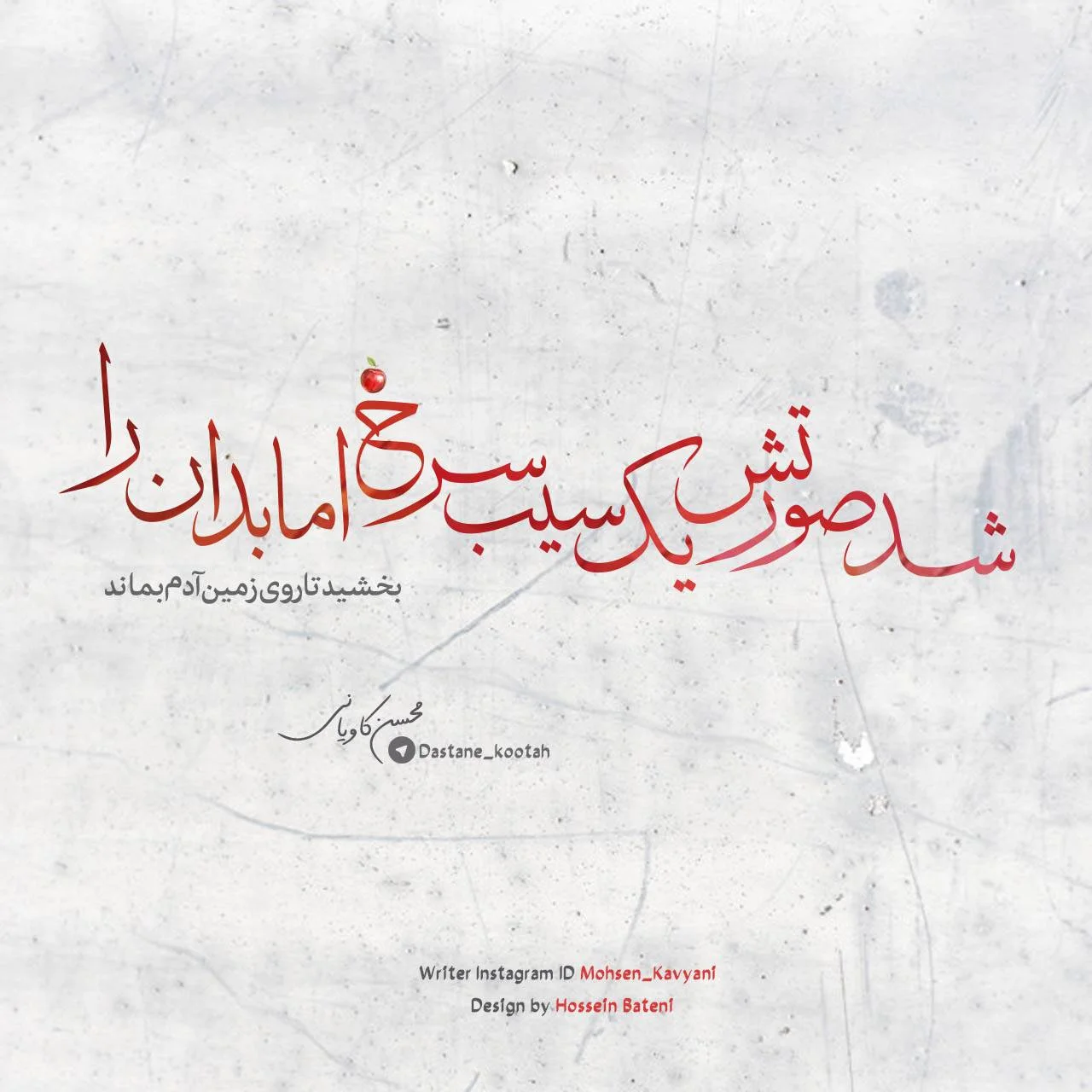
فونت ثلث
یک فونت ثلث واقعی
فونت ثلث واقعی
یک فونت ثلث واقعی
فونت Thulth (Thulth Tharwat Emara Golden) با ساختارهای هنری زیبا و جملات آماده شده به شما کمک می کند تا به راحتی طراحی کنید
Thulth Tharwat Emara Golden Font
همچنین زیبایی خوشنویسی اصلی عربی خود را حفظ می کند ( یک فونت ثلث واقعی  )
Thulth font (Thulth Tharwat Emara Golden) distinguished by beautiful artistic structures and ready-made sentences to help you design the designer designs and paintings easily. It also retains the beauty of its original Arabic calligraphy.